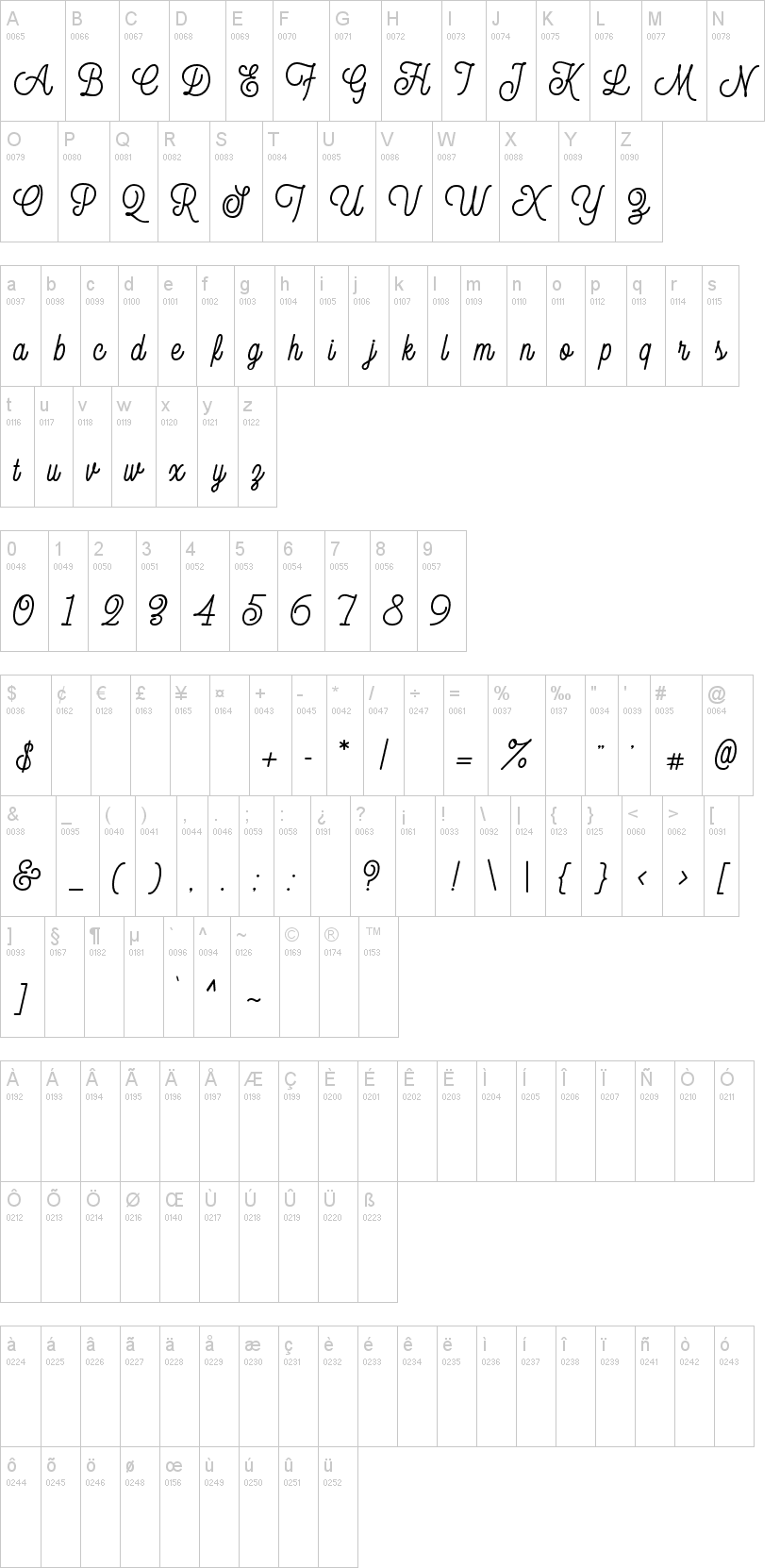
Thirdlone
? Thirdlone 字体是一种简洁、清新、优雅的文字体,它拥有细腻的笔画和精致的字形,可以帮助你创建出更有品质感的文字体。它的设计理念是简约、精致、大方,可以为文字提供更加优雅的外观,适合用于报纸、杂志、书籍、宣传物料等产品的文字表现。
Thirdlone是一款非常不错的手写艺术字体,具有很好的视觉感,适合于文化类的宣传设计、商业类品牌的广告和产品包装设计以及个性化文字排版等较多场景。
Thirdlone字符映射图